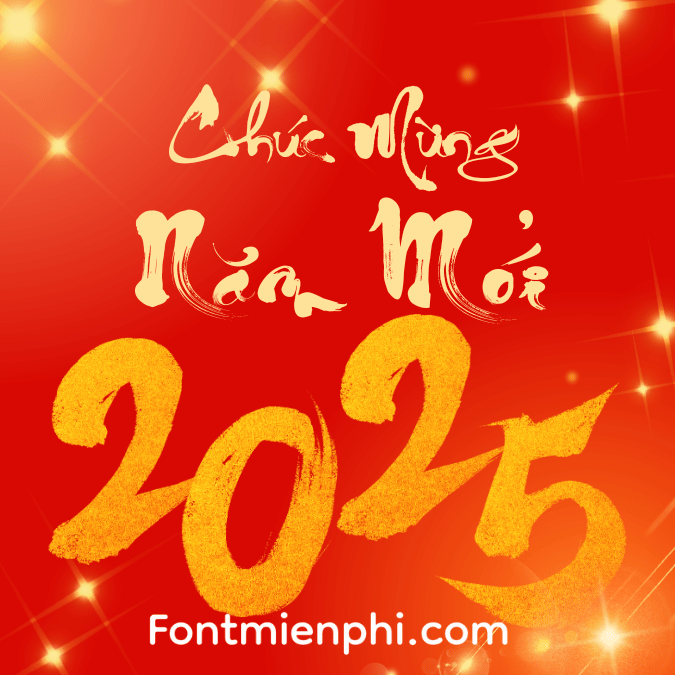
Font thư pháp Thành Công ,font Tết
Font thư pháp Thành Công là một kiểu chữ được thiết kế với phong cách thư pháp truyền thống Việt Nam. Nó mang đến cảm giác thanh thoát, uyển chuyển và sang trọng. Các nét chữ mềm mại, hòa quyện với nhau tạo ra một hình ảnh tinh tế và nghệ thuật. Font này thường được sử dụng trong các dịp lễ hội, thiệp mời, hoặc trong các tác phẩm nghệ thuật biểu diễn, biểu đạt sự kính trọng và trang trọng.
Mô tả Font Tết
Font Tết là kiểu chữ mang đậm không khí Tết Nguyên Đán, thể hiện sự vui tươi và phấn khởi của mùa xuân. Với những đường nét mềm mại và màu sắc rực rỡ, font này thường được sử dụng trong các thiệp chúc Tết, banner quảng cáo, và trang trí nhà cửa trong dịp lễ. Nó gợi lên cảm giác ấm áp, hạnh phúc và sum vầy của gia đình trong những ngày đầu năm mới.
Cả hai font đều có thể được sử dụng để tạo nên những sản phẩm thiết kế độc đáo và ý nghĩa trong các dịp lễ hội và sự kiện đặc biệt.